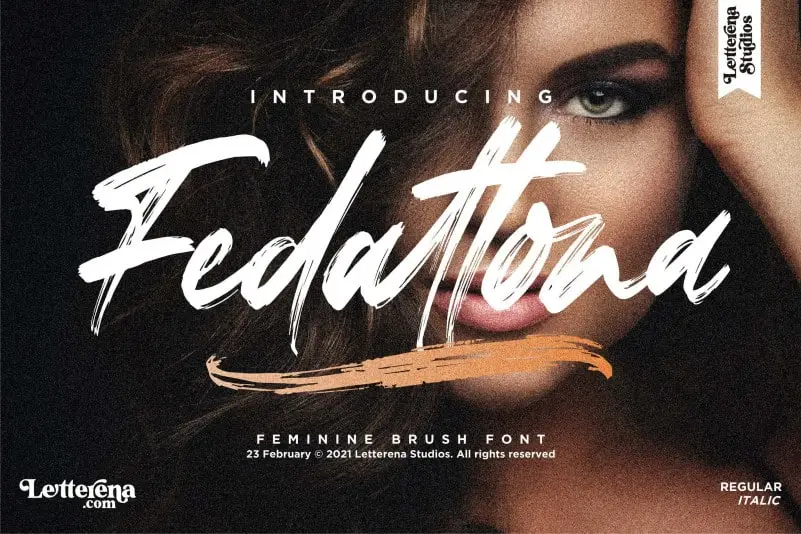
Fedattona Brush Font – Download Grátis
Fedattona Brush Font é uma escolha perfeita para designers que buscam adicionar personalidade e sofisticação a seus projetos. Criada pela Letterena Studios, esta fonte script é um verdadeiro convite ao design, com suas curvas espontaneamente delineadas pelo uso de canetas-pen. A característica mais marcante é o contraste perfeito entre as curvas finas e grossas que ela proporciona, tornando-a ideal para uma ampla gama de projetos, desde logomarcas e identidades visuais até embalagens de produtos, prateleiras em cafés e carteiras personalizadas. Fedattona Brush é especialmente apropriada para qualquer projeto onde você deseja adicionar um toque delicado e elegante, seja ele uma capa de livro ou cartão de convite especial para eventos memoráveis. Suas linhas fluidas e sua simplicidade única garantem que ela se destaque em todos os projetos que a usam.